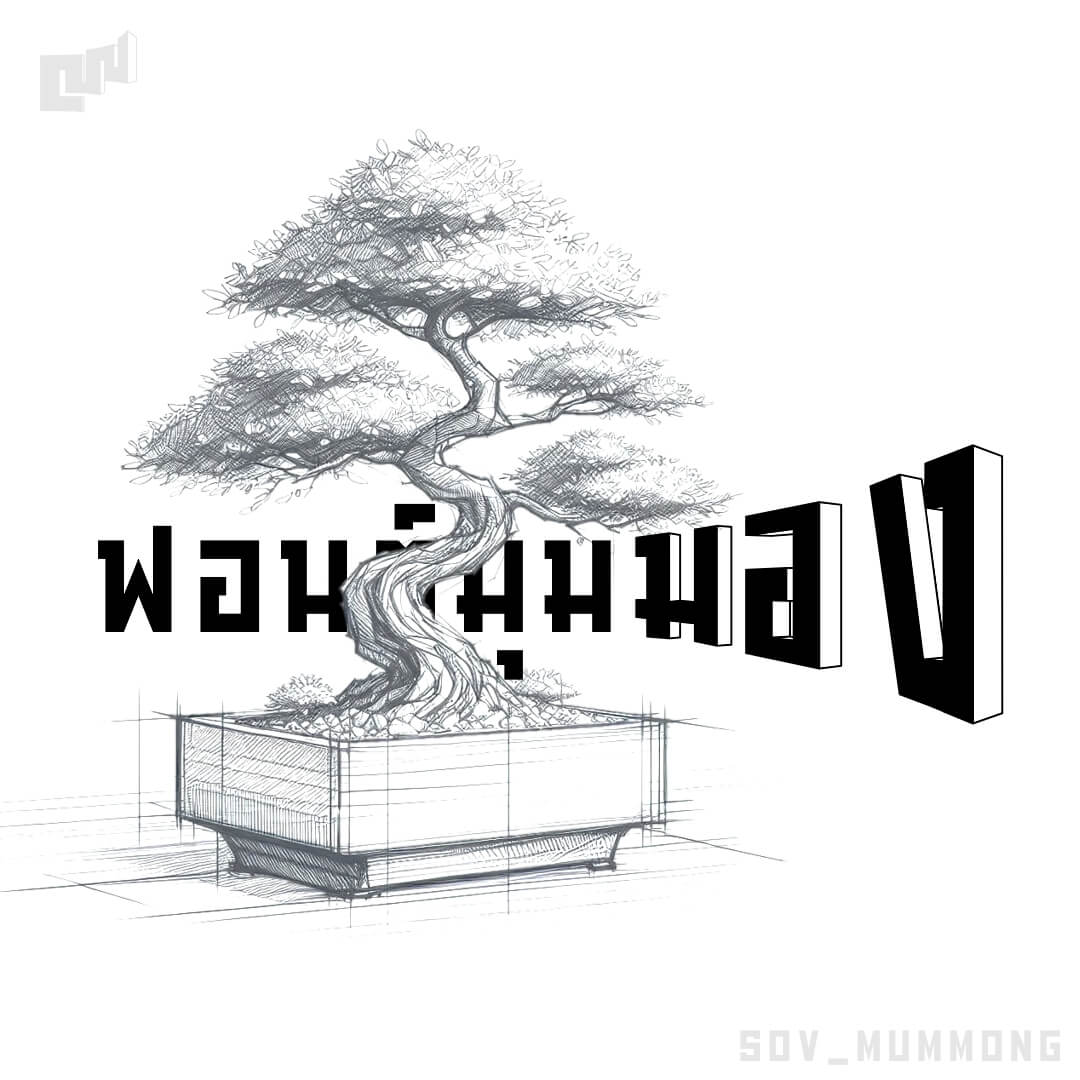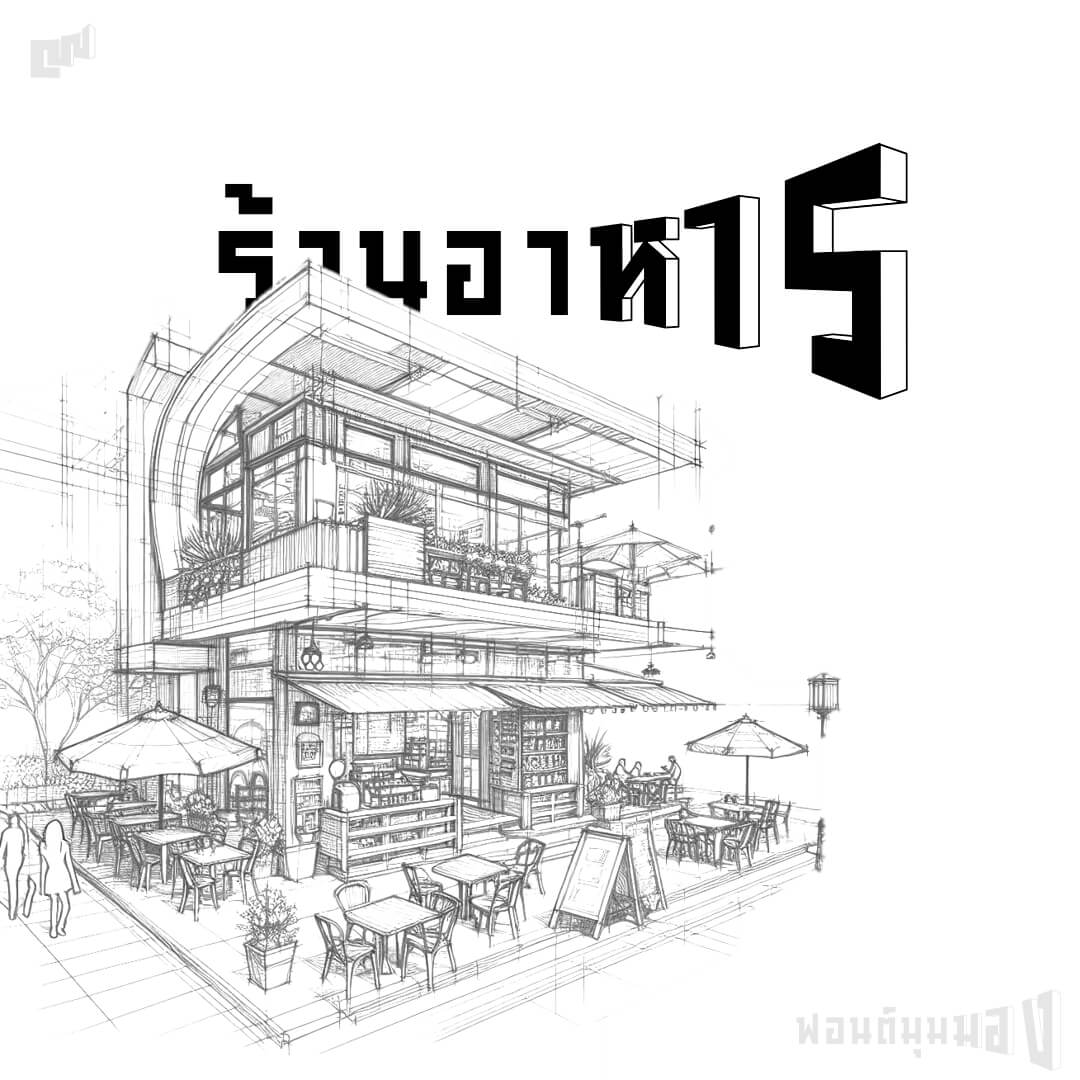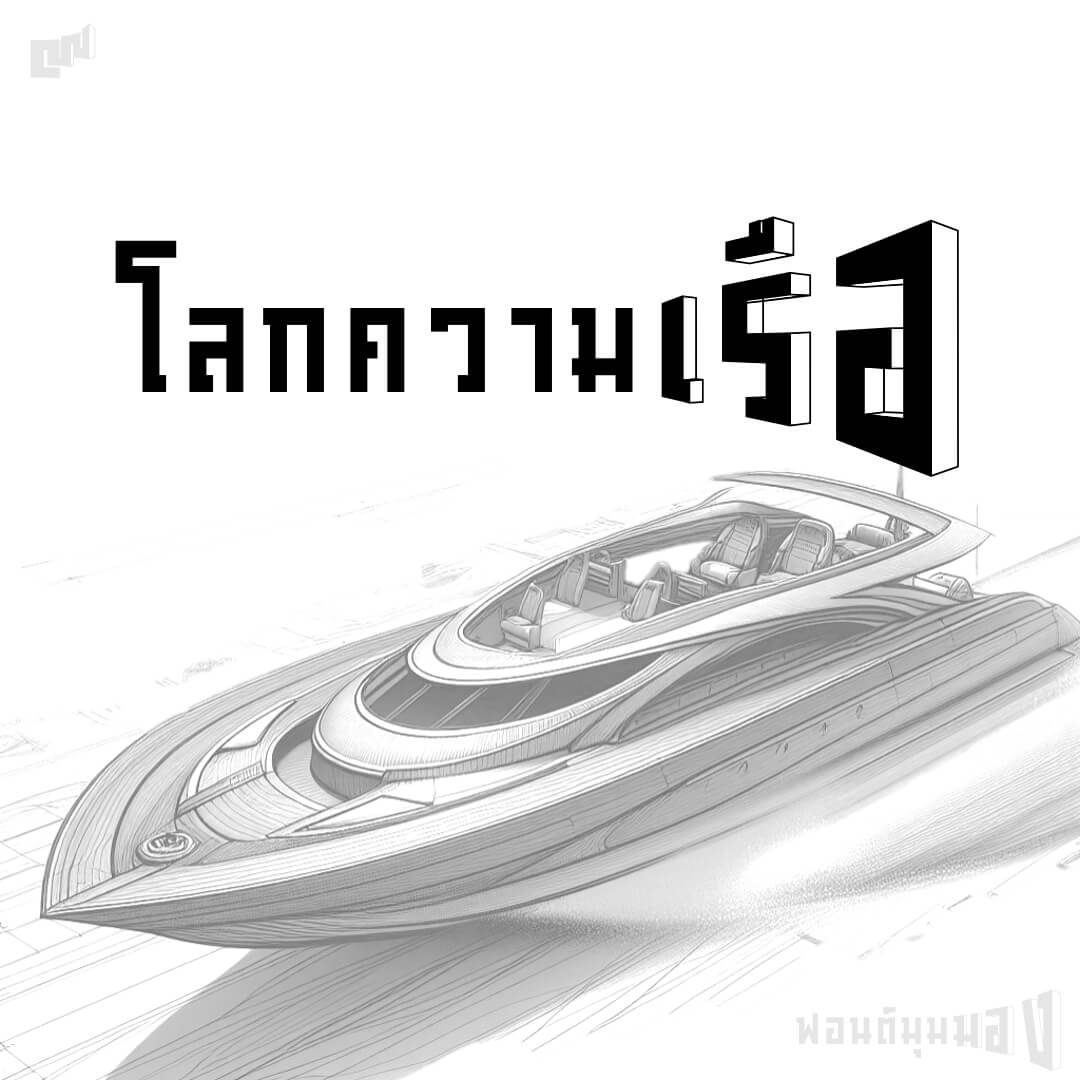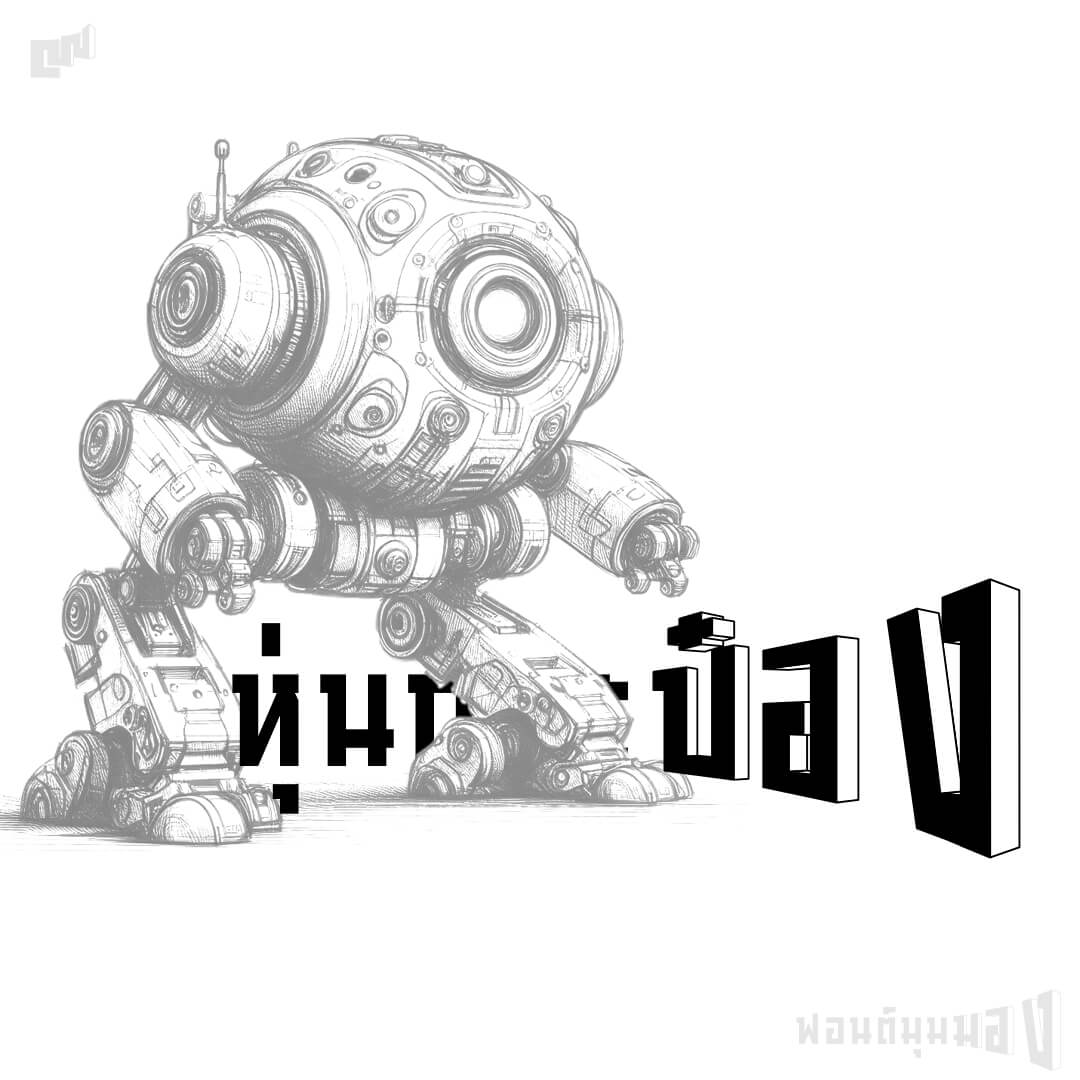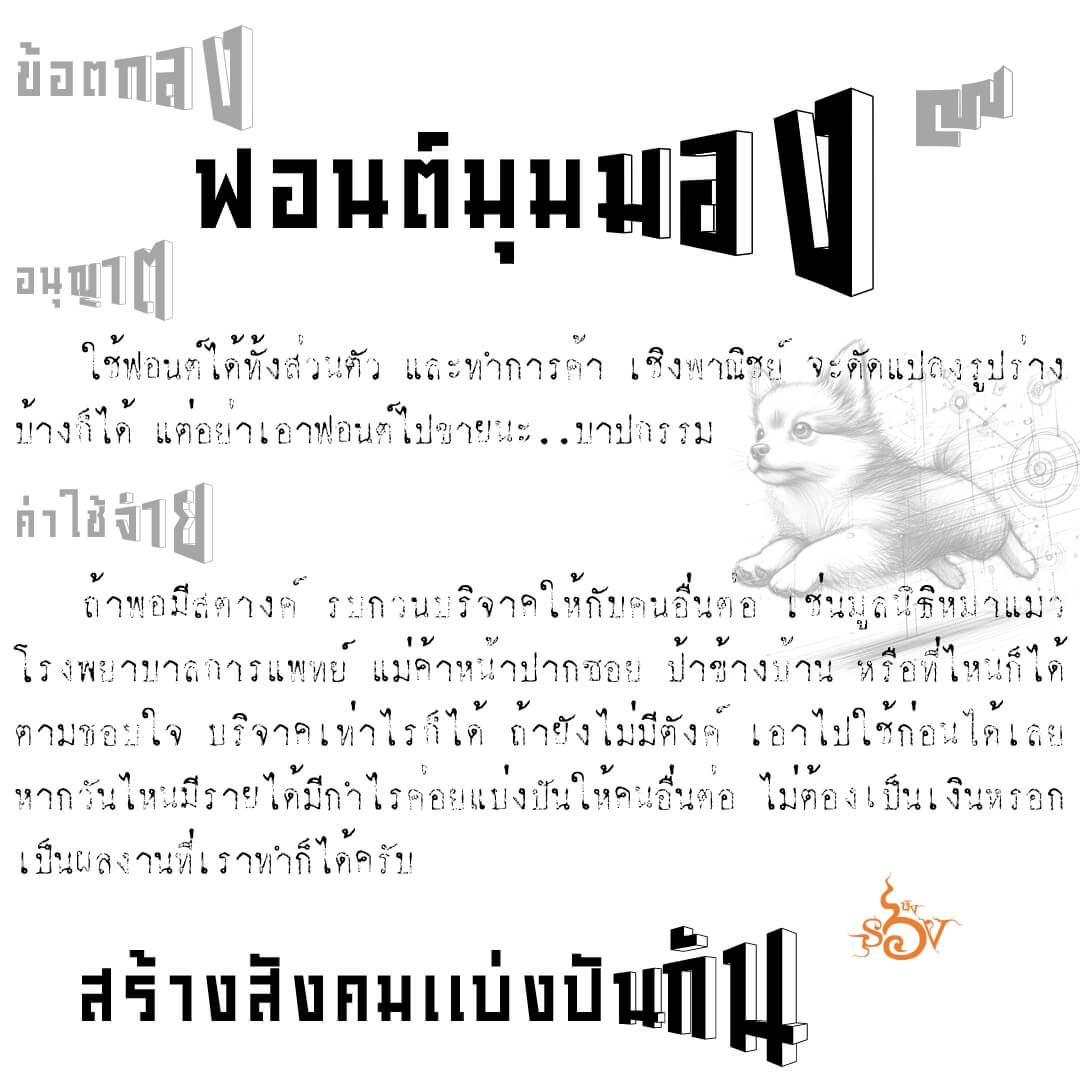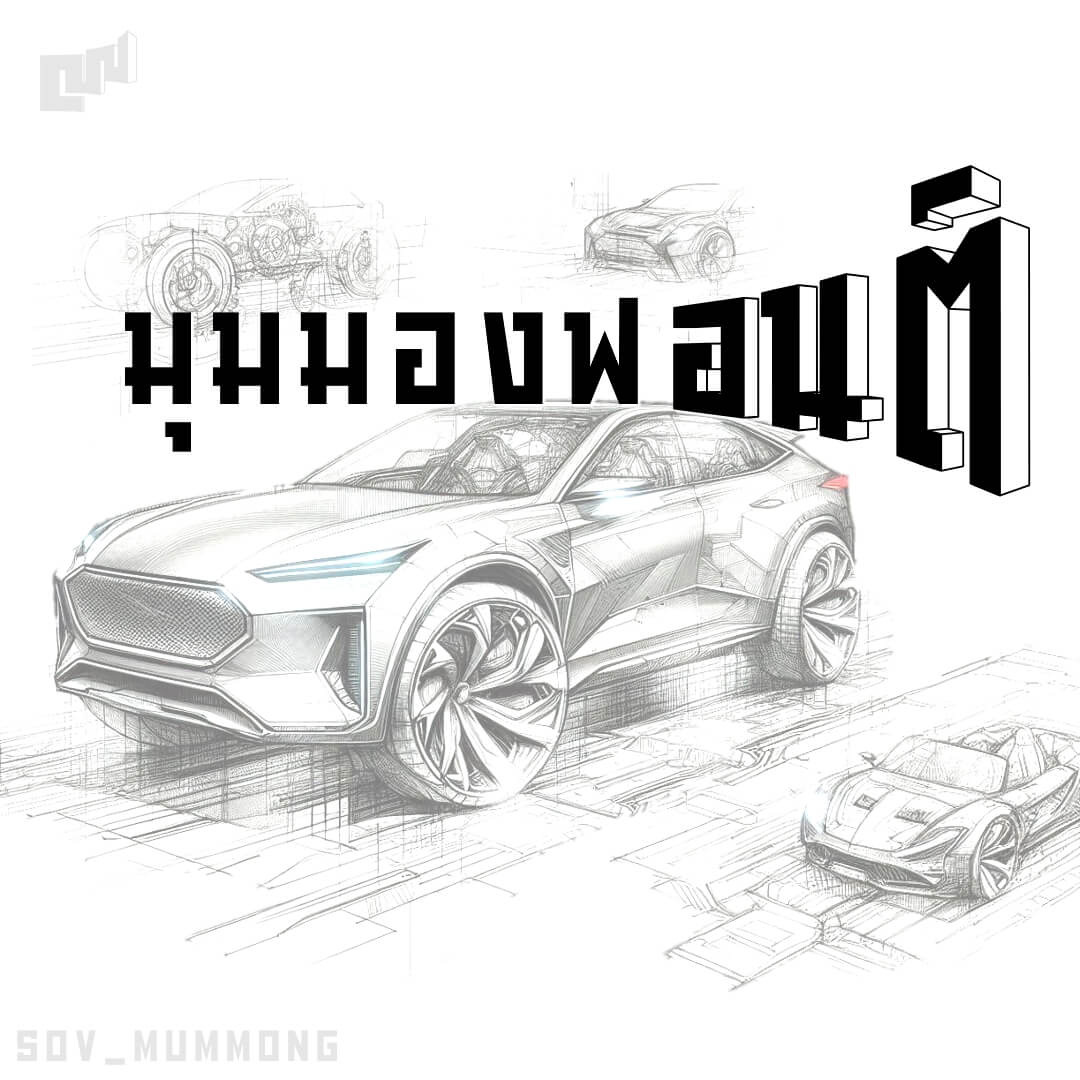
ฟอนต์มุมมอง – ทดลองทำฟอนต์ perspective ไม่ใช่แค่ตัวอักษร แต่เป็นประโยค… ปัญหาใหญ่คือเขียนได้ไม่กี่ตัวอักษรขนาดหัวแถวหางแถวก็จะต่างกันลิบลับ จึงมีการปรับให้ตัวไกลกลายเป็นแถวตรง เหมือนมุมที่เรามองอยู่ริมทางโค้ง
เบื้องหลังการออกแบบ : ฟอนต์ มุมมอง
มุมมอง (SOV_MumMong)